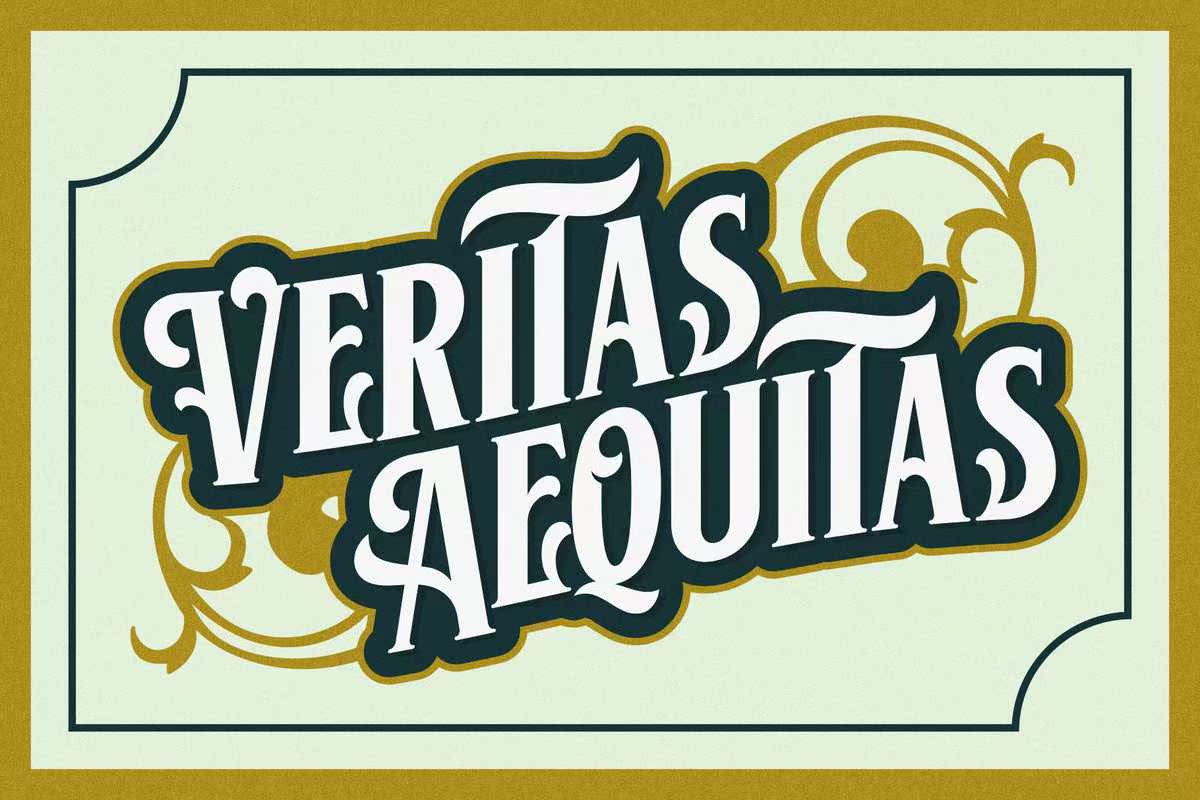
让我们在2019年引入第一方;Cairlin.Acleanserif,被葡萄酒风格的精神所遗忘。深受古典音乐中使用的字母的启发。--PS:这种字体是一种数字版本,它只包含标准字符(大写、小写、数字和标准标点符号)。购买完整/商业版本以获得灯笼/斜体版本、多语言字符,很多OpenTypeCharacters,艾切丽。--谢谢你!让我们在2019年引入第一方;Cairlin.Acleanserif,被葡萄酒风格的精神所遗忘。深受古典音乐中使用的字母的启发。--PS:这种字体是一种数字版本,它只包含标准字符(大写、小写、数字和标准标点符号)。购买完整/商业版本以获得灯笼/斜体版本、多语言字符,很多OpenTypeCharacters,艾切丽。--谢谢你!